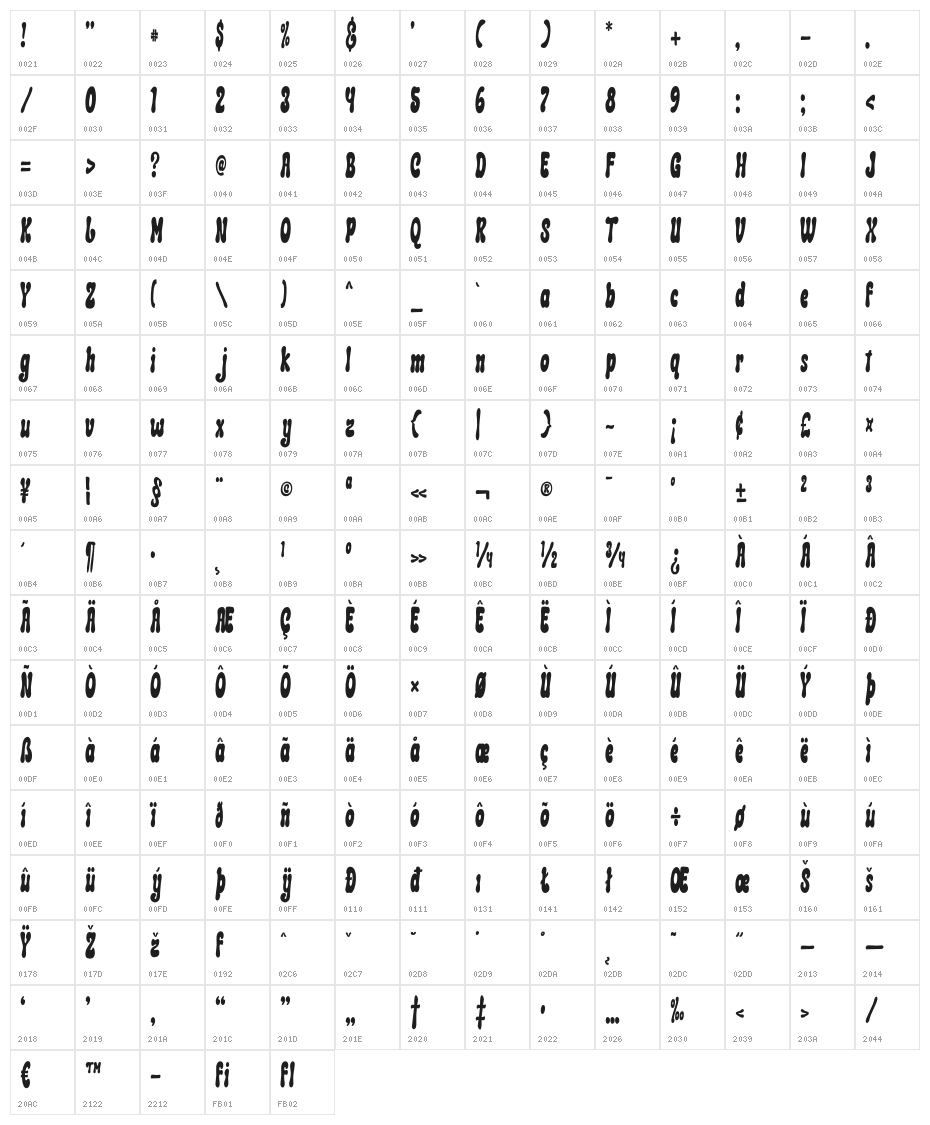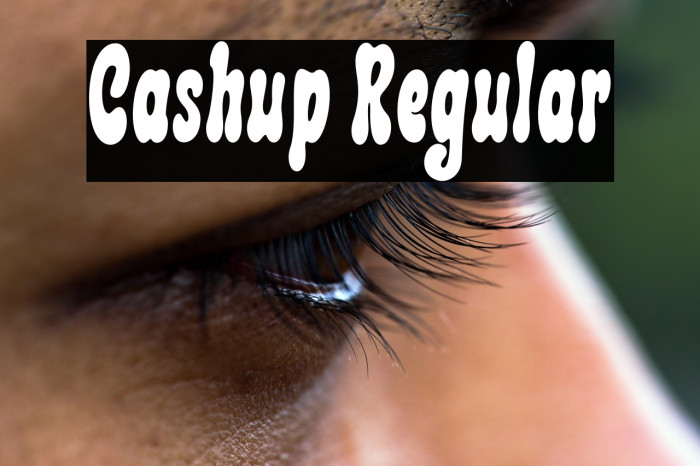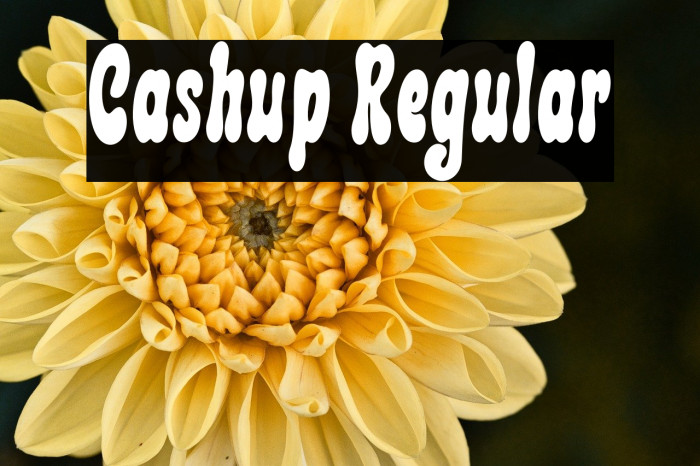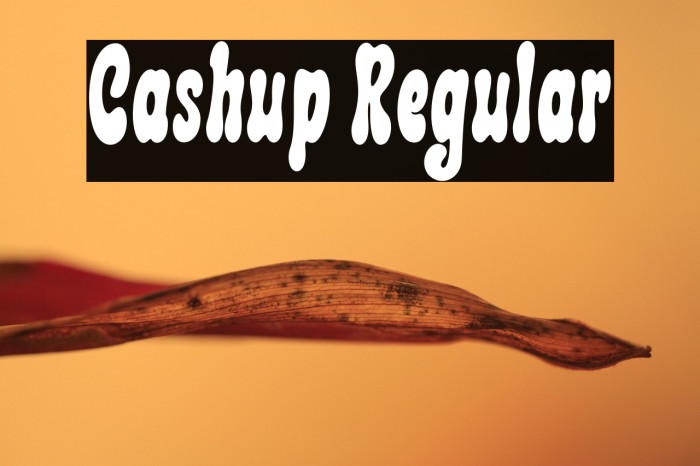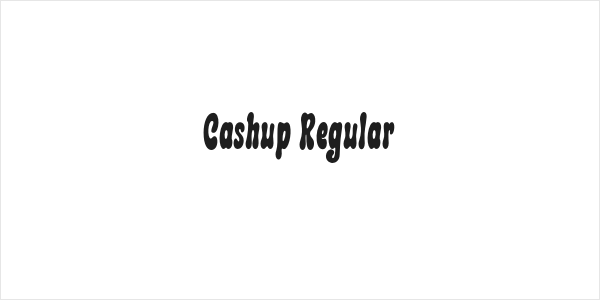
Cashup Regular Font
| Projetos propostos | Ideal for branding, web design, advertising, and editorial projects where clarity and modernity are key. |